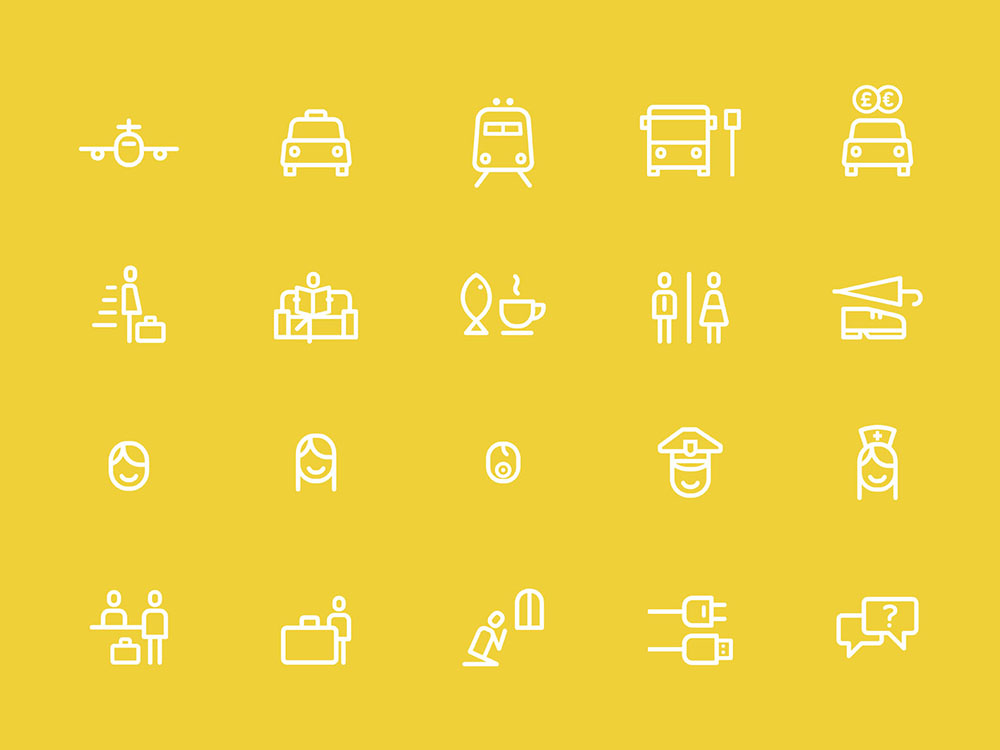
Mejorar la experiencia del pasajero
Los aeropuertos, como lugares de paso, pueden ser fríos y sin personalidad. A esa percepción distante se suma el desasosiego de los pasajeros. La nueva imagen del aeropuerto de Luton (Reino Unido) trata de crear una atmósfera atractiva y acogedora. Los elementos de señalización creados por Atipo buscan mejorar la experiencia del pasajero para que el viaje comience desde el mismo aeropuerto, incluso antes de que el avión llegue a despegar.
El estudio asturiano Atipo ha sido el encargado de desarrollar la tipografía y la iconografía de la nueva identidad del aeropuerto londinense de Luton. El proyecto se encuadra dentro del rebranding llevado a cabo por la agencia británica Ico Design que persigue redefinir el posicionamiento de la terminal aérea frente a los otros aeropuertos de la capital a través de un diseño orientado al usuario.
Una tipografía técnica pero con un punto humanista
El proceso de diseño de LLA, nombre que recibe la nueva tipografía, se llevó a cabo a lo largo de tres meses dividido en diferentes etapas. Su resultado fue fue el uso de una fuente que aúna las referencias clásicas de familias tipográficas como la DIN, la Helvética o la Frutiger y el espíritu contemporáneo de la Neo o la Simple; logrando así un equilibrio entre funcionalidad y personalidad. Gracias a su estructura condensada LLA permite economizar el espacio encajando la mayor cantidad de texto en la menor superficie posible. Su gran altura y las amplias contraformas resuelven eficazmente el efecto negativo que una excesiva condensación provocaría en su legibilidad, aspecto esencial para una fuente destinada a la señalización. Asimismo, las formas abiertas, como en el caso de las minúsculas (a, e, g, s), facilitan su diferenciación de letras más cerradas como la “o”. Estos tipos de palo seco, presentan ascendentes mayores que las mayúsculas y terminales redondeados, dotando así a la fuente de un aspecto contemporáneo. LLA posee, según sus creadores, “un aire técnico pero con un punto humanista”. El proyecto del estudio asturiano se completa con un conjunto de iconos diseñados para la señalética del aeropuerto londinense. Su diseño responde a la búsqueda de una imagen más amable y eficiente a través de representaciones flexibles y sencillas. Ico Design propuso que las imágenes fuesen dibujadas a mano y presentasen un punto amable. La “o” minúscula sirvió como base para la creación de los iconos, logrando así que la tipografía y la iconografía estuvieran alineadas y funcionasen como una familia.
Sobre Atipo
Atipo, fundado por Raúl García del Pomar e Ismael González a principios de 2010, se presenta como un estudio multidisciplinar especializado en Diseño Gráfico con base en Gijón (Asturias, España). El estudio cuenta con varios galardones, entre los que cabe destacar dos Laus de Oro, un Brand New Award, un European Design Award y varios premios Motiva. Su filosofía se centra en ofrecer soluciones basadas en un diseño sencillo, funcional y coherente, donde la idea se anteponga a la estética.
En detalle: la visión de los autores
“El desarrollo de cualquier fuente comprende diferentes fases: dibujo de los glifos, ajustes, diseño del espaciado, el kerning, la programación opentype, la creación de los diferentes pesos y comprobar que todo funciona perfectamente”, señala Ismael González, fundador de Atipo. “Hay ocasiones en las que a la hora de plantear un estilo de iconos se puede ser más experimental o arriesgado, pero estamos hablando de usos muy concretos, como puede ser los iconos de los baños de una discoteca o un restaurante; pero en esta ocasión prima la funcionalidad, la iconografía tiene que ser reconocible por cualquier persona, puesto que estamos hablando de la señalización de un aeropuerto y ante todo ha de cumplir una misión informativa”, comenta Ismael González.